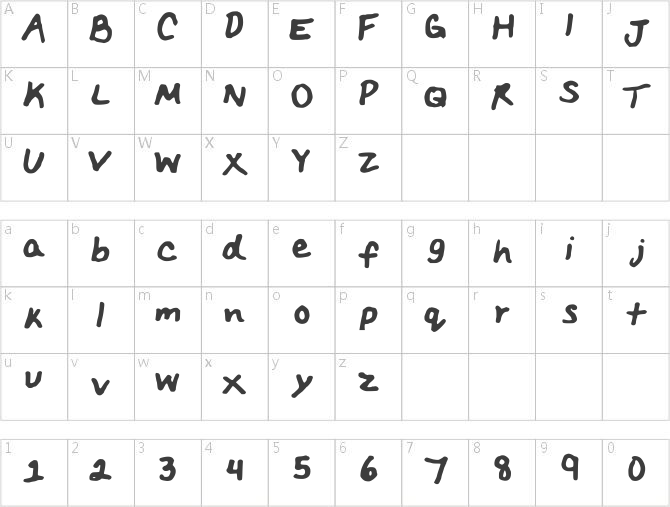
Camden_Boyd_Regular 詳情頁
Camden_Boyd_Regular
Camden_Boyd_Regular字體字庫是一款讓人賞心悅目、百看不厭的英文字體,適合各類廣告和產(chǎn)品包裝設(shè)計(jì)應(yīng)用,字體大小0.03MB,格式為ttf字體,上傳用戶是一直在守護(hù),作者/版權(quán)方為未知